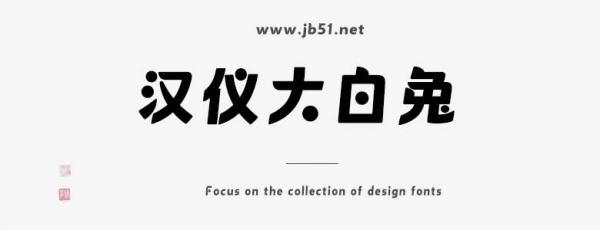
漢儀大白兔是由漢儀字庫出品,字體筆觸適中,在傳承大白免品牌經(jīng)典設(shè)計(jì)元素的基礎(chǔ)上,整體風(fēng)格更加簡潔,適合應(yīng)用于藝術(shù)設(shè)計(jì)、平面宣傳設(shè)計(jì)、網(wǎng)頁設(shè)計(jì),書法字帖等領(lǐng)域,需要的朋友可以前來本站下載。